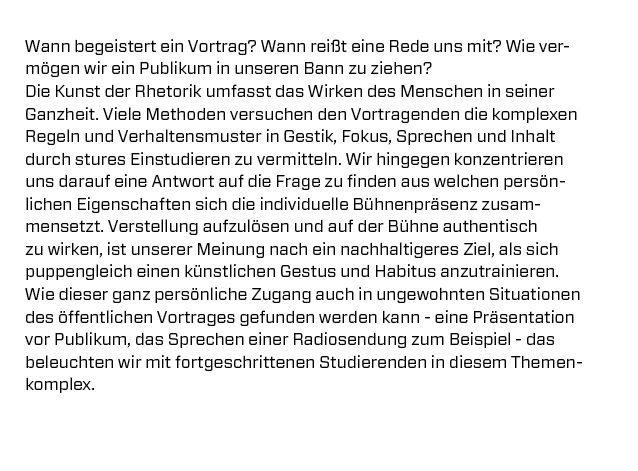
Vitesse/Forza - passende Fliesstextschrift gesucht!
Für einen Kunden habe ich ein Corporate Design entwickelt, welches auf der Vitesse/Forza beruht. Sieht im Logo und für Headlines gut aus, allerdings bin ich etwas skeptisch, was die Anwendung der Forza im Fliesstext angeht. Ist irgendwie etwas zu eckig ... was meint ihr? http://www.typography.com/fonts/forza/overview/
Hat jemand vielleicht einen guten Vorschlag für eine dazu pasende Serifenlose Schrift als Ergänzung?
ja würde ich auch nicht für Fließtexte einsetzen.
Kannst Du noch etwas zum Thema/Inhalt verraten? Das macht die Eingrenzung auf passende Serifenlose etwas einfacher.
Eines steht jedoch schonmal fest, eine weitere Serifenlose mit – wenn auch nicht so ausgeformtem – eckigem Gerüst (Camingo Dos, Klavika, FF Clan) hielte ich vor allem aufgrund mangelndem Kontrast nicht für sinnvoll. Ich würde eher zu einer schlichten statischen, dynamischen oder geometrischen Grotesk tendieren (Hoefler selbst empfiehlt übrigens Gotham narrow).
vielen Dank schon einmal für deine Antwort! Denke auch, dass eine relativ schlichte Serifenlose Sinn machen würde und finde die Gotham Narrow schon recht geeignet. Thematisch/Inhaltlich geht es um ein junges Unternehmen aus dem Bereich der nachhaltigen Chemie. Also würden es die Attribute modern, sachlich, aber auch mit ein freundlichem, sympathischen Unterton versehen ganz gut treffen. Hauptsächlich muss die Schrift aber einfach funktionieren, Funktionsträger sein. Wahrscheinlich ist ein eigenständiger Charakter auch nicht so gut, da ja die Vitesse/Forza als Displayschrift verwendet werden wird und da schon recht stark ist...
Wahrscheinlich ist ein eigenständiger Charakter auch nicht so gut, da ja die Vitesse/Forza als Displayschrift verwendet werden wird und da schon recht stark ist...
Genauso sehe ich das auch. Wenn Du es etwas »wärmer« als bei der Gotham haben möchtest, könntest Du eventuell hier noch Kandidaten finden:
Statische Alternativen zur Arial – neutrale bis sachlich-schlichte Serifenlose
Oder man versucht es mal mit einer Schrift der Kategorie FS Matthew oder FF Scuba – müsste man sich mal anschauen.
danke für deine Tipps, die werde ich mir mal ansehen! Ich würde eine Serif/Slab nicht grundsätzlich auschliessen - allerdings ist schon die Vitesse als Slab im Logo enthalten ... meinst du nicht, dass eine weitere/andere Slabserif da zu nah dran wäre stilistisch?